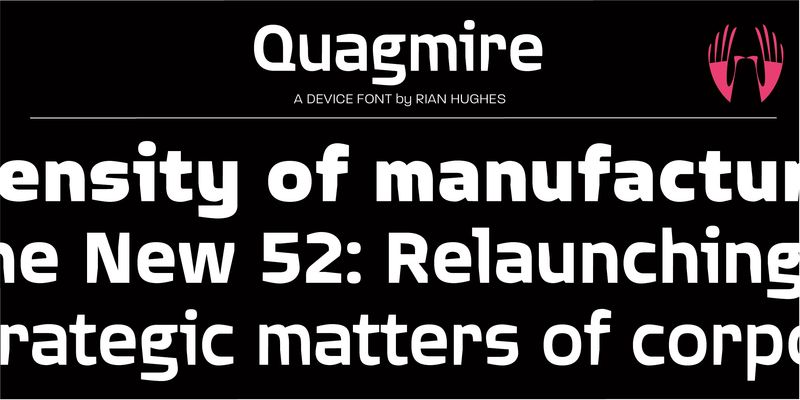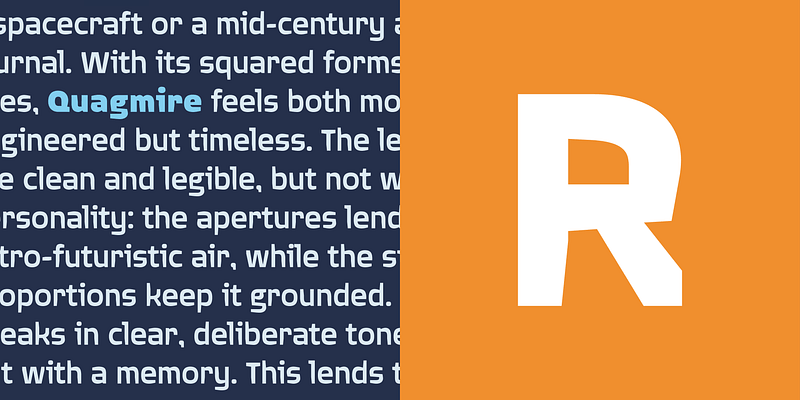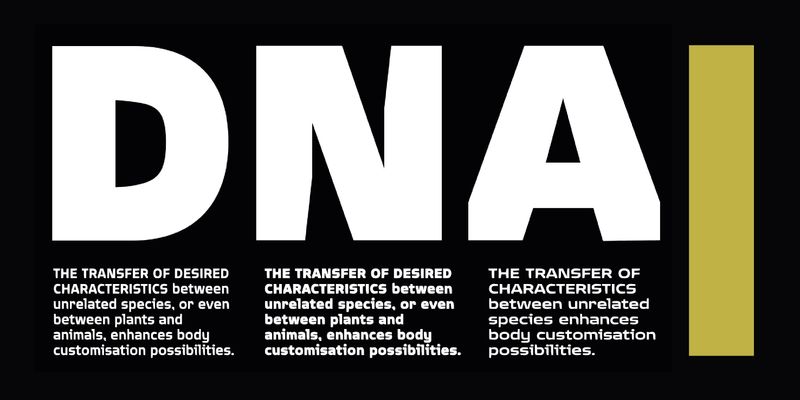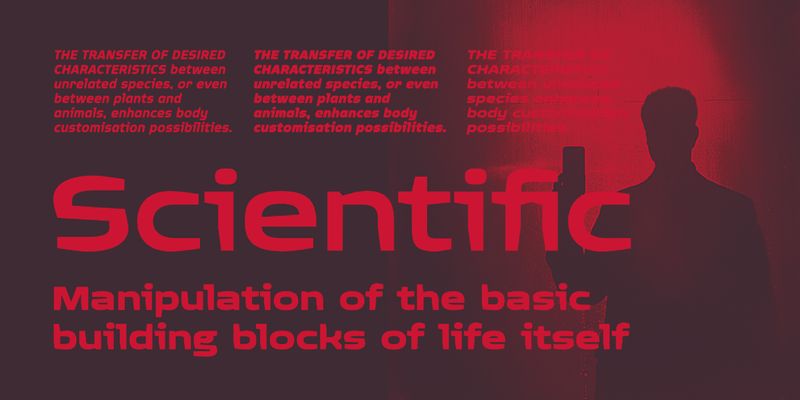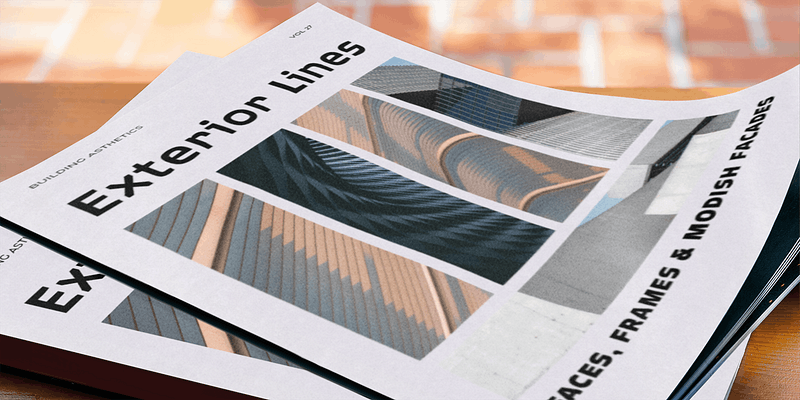
Eine vielseitige, moderne Sans mit genügend Charakter, um sie aus dem Gewöhnlichen herauszuheben, während sie in längeren Sätzen lesbar bleibt. Sauber, scharf, frisch.
Schrift, Design und Bilder stammen vom englischen Illustrator und Typografen Rian Hughes.